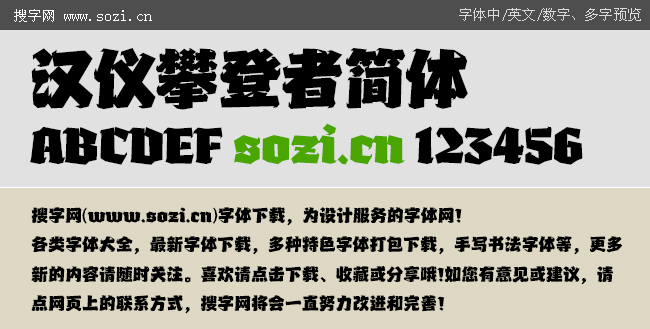
漢儀攀登者簡(jiǎn)體
搜字網(wǎng)給大家提供一款漢儀攀登者簡(jiǎn)體中文字體下載,漢儀攀登者簡(jiǎn)體是一套廣告POP字體,字體筆觸鮮明,字形夸張醒目,筆畫可愛灑脫,結(jié)構(gòu)充滿變化,非常有趣味性。適用于畫冊(cè)設(shè)計(jì)、海報(bào)設(shè)計(jì)、包裝設(shè)計(jì)等場(chǎng)合使用。(本字體為個(gè)人非商用版,如需要商用請(qǐng)聯(lián)系漢儀公司購(gòu)買版權(quán))